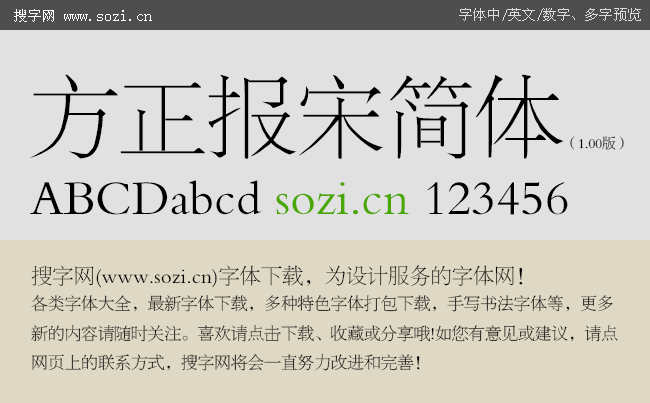
方正報(bào)宋簡(jiǎn)體
搜字網(wǎng)提供一款方正報(bào)宋簡(jiǎn)體中文字體下載,方正報(bào)宋簡(jiǎn)體是一款非常端正的中文字體,適合在正式的場(chǎng)合來(lái)進(jìn)行使用,適合應(yīng)用于廣告設(shè)計(jì)、名片設(shè)計(jì)、包裝印刷、產(chǎn)品設(shè)計(jì)等應(yīng)用。